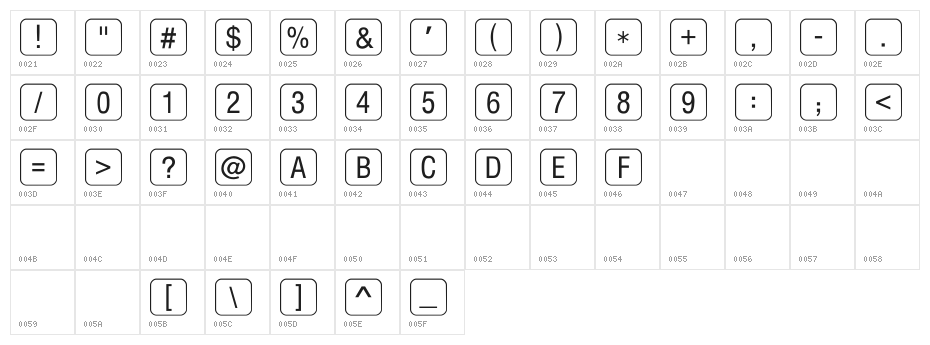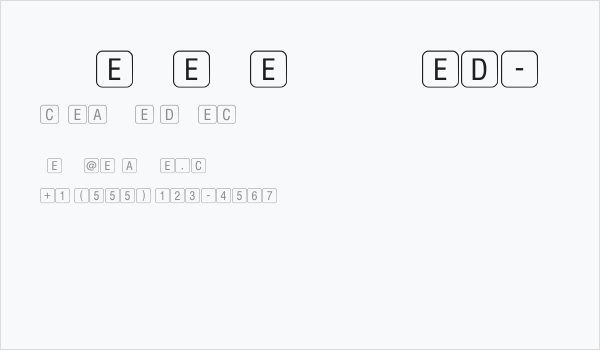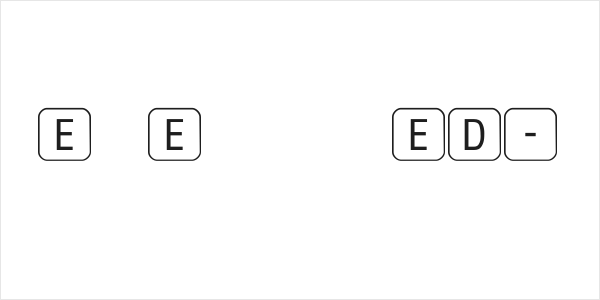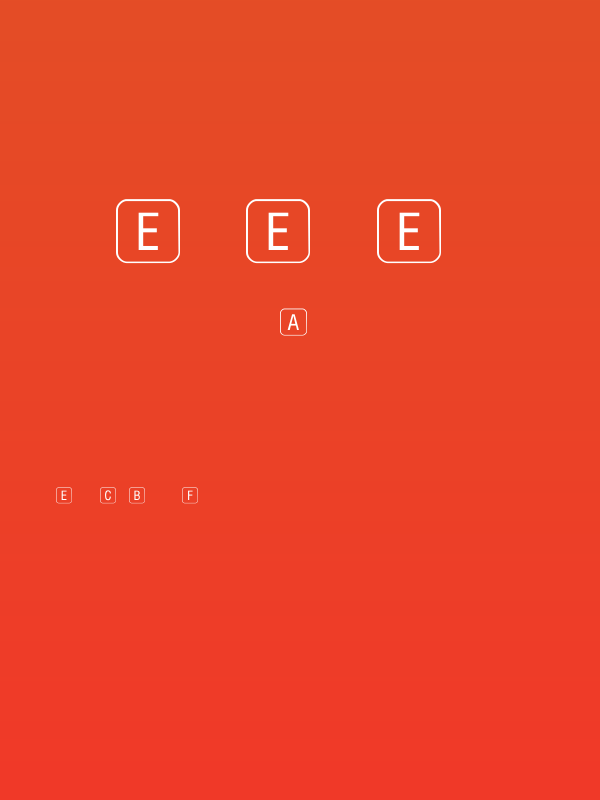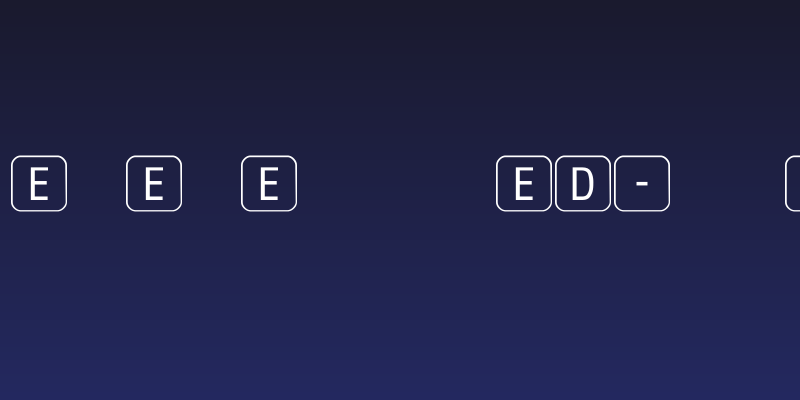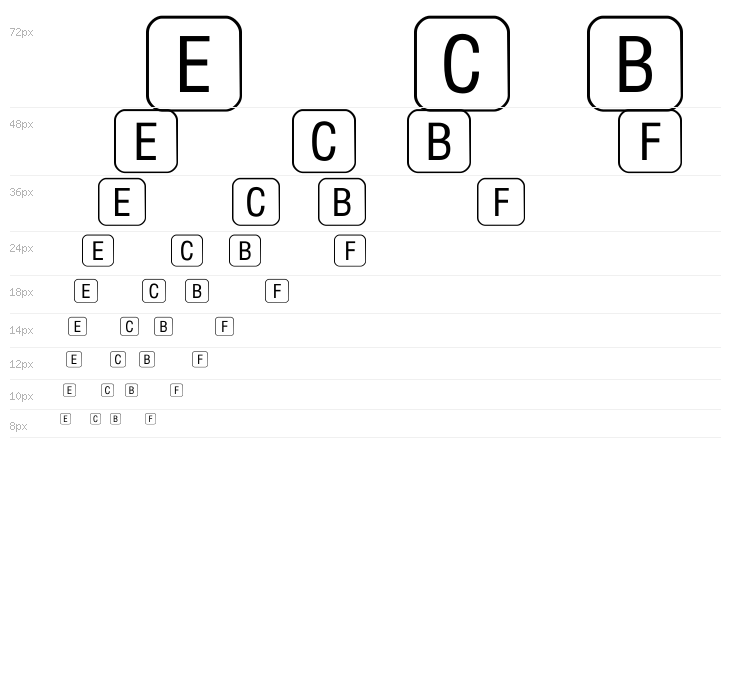
RRKeyLettersLimited-Normal Font
✎ Technical
| Categorie | Technical |
| Caso d'uso | Headlines, Logos, Signage |
| Progetti proposti | Ideal for retro-themed designs, branding, signage, and any project requiring a mechanical or typewriter-inspired aesthetic. |